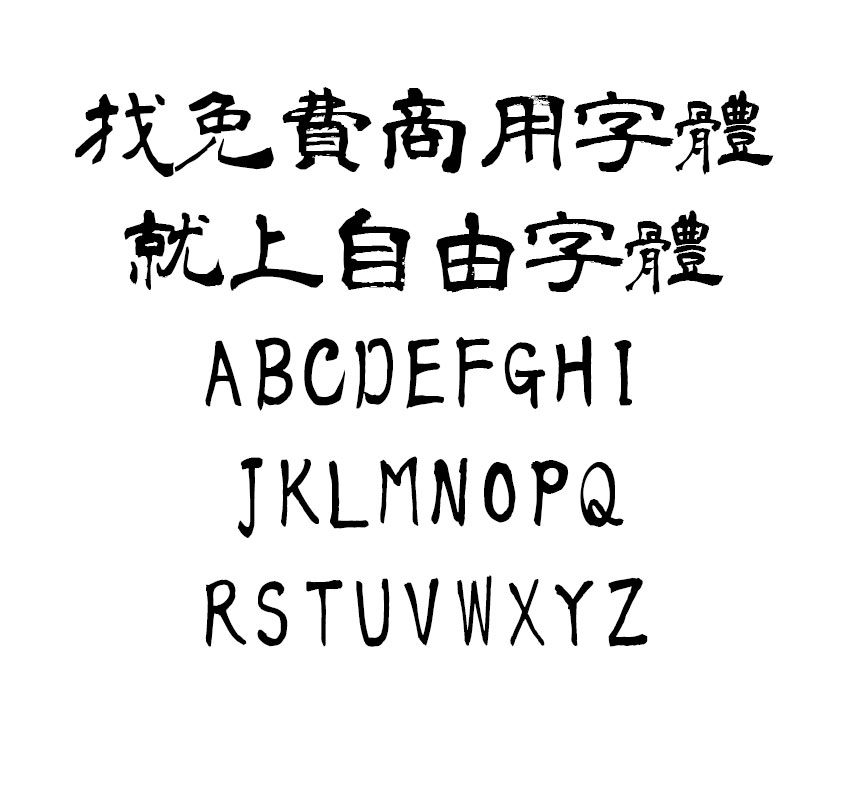
青柳隶书
青柳隶书(青柳隷書しも / 青柳隷書SIMO2_T / aoyagireisyosimo2)是日本书法家青柳衡山老师题字的,然后是SIMO先生制作成TrueType字体。这款字体包含JIS第1水准2965字,第2水准3390字。
由于字体采用的日本的JIS标准,所以支持的简体字数不算多,但是繁体却是比较齐全的。隶书的免费字体很少见,所以对古典风格的设计等很有用。